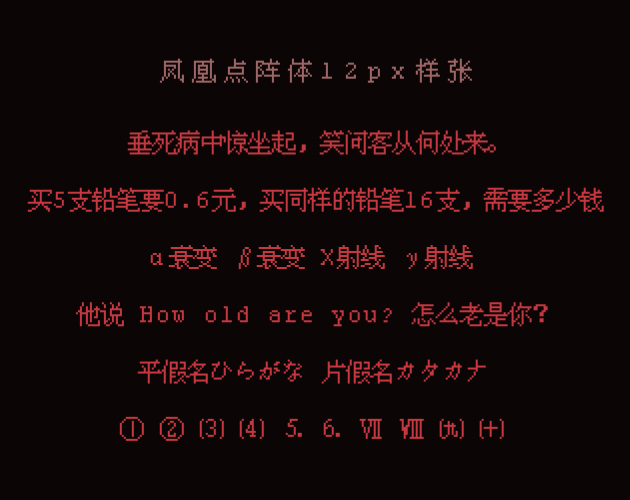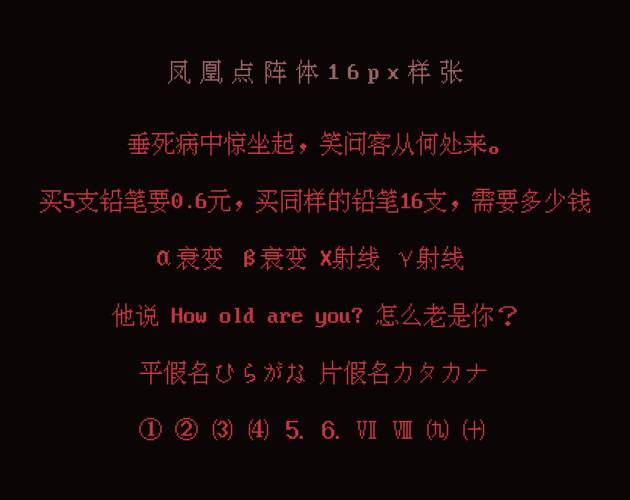
鳳凰點陣體(Vonwaon Bitmap)是免費的中文像素字體,使用 CC0 1.0協議發佈,屬於公有領域。字模基於開源項目 BitmapFont,針對漢字與非漢字、不同字號、字體之間的搭配進行了優化。
壓縮包有 12px 和 16px 兩個版本的字體(對應 9pt 和 12pt),這是它們各自使用的基準字模的像素高度。
鳳凰點陣體共包含 7543 個字符,其中漢字 6763 個。如果你非常在乎文件大小,使用 Lite 版,共包含 4041 個字符,其中漢字可以 3755 個(省略了簡化使用的二級漢字)。版不包含日文假名、希臘字母、俄文字母、拼音、注音符號、製表字符、以及順序字符。